Font chữ cho tem bảo hành, nhãn kỹ thuật và bao bì điện tử
Gợi ý font TH Việt hóa rõ ràng cho tem bảo hành, nhãn kỹ thuật, bao bì điện tử, bảng thông số sản phẩm và label kỹ thuật.
Tem bảo hành, nhãn kỹ thuật và bao bì điện tử là nhóm thiết kế nhỏ nhưng rất dễ lộ lỗi typography. Chỉ cần font khó đọc ở cỡ 6-9pt, thông số sản phẩm, mã serial, ngày bảo hành, QR code hoặc cảnh báo an toàn có thể trở nên rối và thiếu chuyên nghiệp. Với sản phẩm điện tử, font chữ cần tạo cảm giác chính xác, sạch, đáng tin và in ra vẫn rõ.
Bài viết này gợi ý cách chọn font nhãn kỹ thuật Việt hóa cho tem bảo hành, tem phụ, bao bì điện tử, bảng thông số sản phẩm, label kỹ thuật, warranty card và tài liệu hướng dẫn đi kèm. Danh sách ưu tiên các font TH sans-serif, font công nghệ và font dễ đọc ở kích thước nhỏ, khác nhóm sport/streetwear của bài áo thun trước đó.
Font nhãn kỹ thuật cần đáp ứng điều gì?
Đầu tiên là độ đọc. Nhãn kỹ thuật thường có nhiều chuỗi ngắn như model, SKU, input/output, dung lượng pin, điện áp, ngày sản xuất, số seri và thông tin bảo hành. Font cần có chữ số rõ, khoảng cách ký tự vừa đủ và dấu tiếng Việt không bị dính. Thứ hai là khả năng in. Nếu in tem nhỏ, tem decal, in offset hoặc in lụa lên vỏ hộp, font quá mảnh hoặc quá trang trí sẽ dễ mất nét.
Thứ ba là cảm giác thương hiệu. Bao bì điện tử nên gọn, hiện đại, nhưng không nhất thiết phải quá lạnh. Với thiết bị thông minh, font công nghệ sẽ hợp cho headline. Với nhãn hướng dẫn cho người dùng phổ thông, sans-serif trung tính và thân thiện sẽ an toàn hơn.
Gợi ý font TH cho tem bảo hành, nhãn kỹ thuật và bao bì điện tử
1. TH Gyokz - nhãn công nghệ, tem bảo hành điện tử, headline nhỏ trên hộp thiết bị
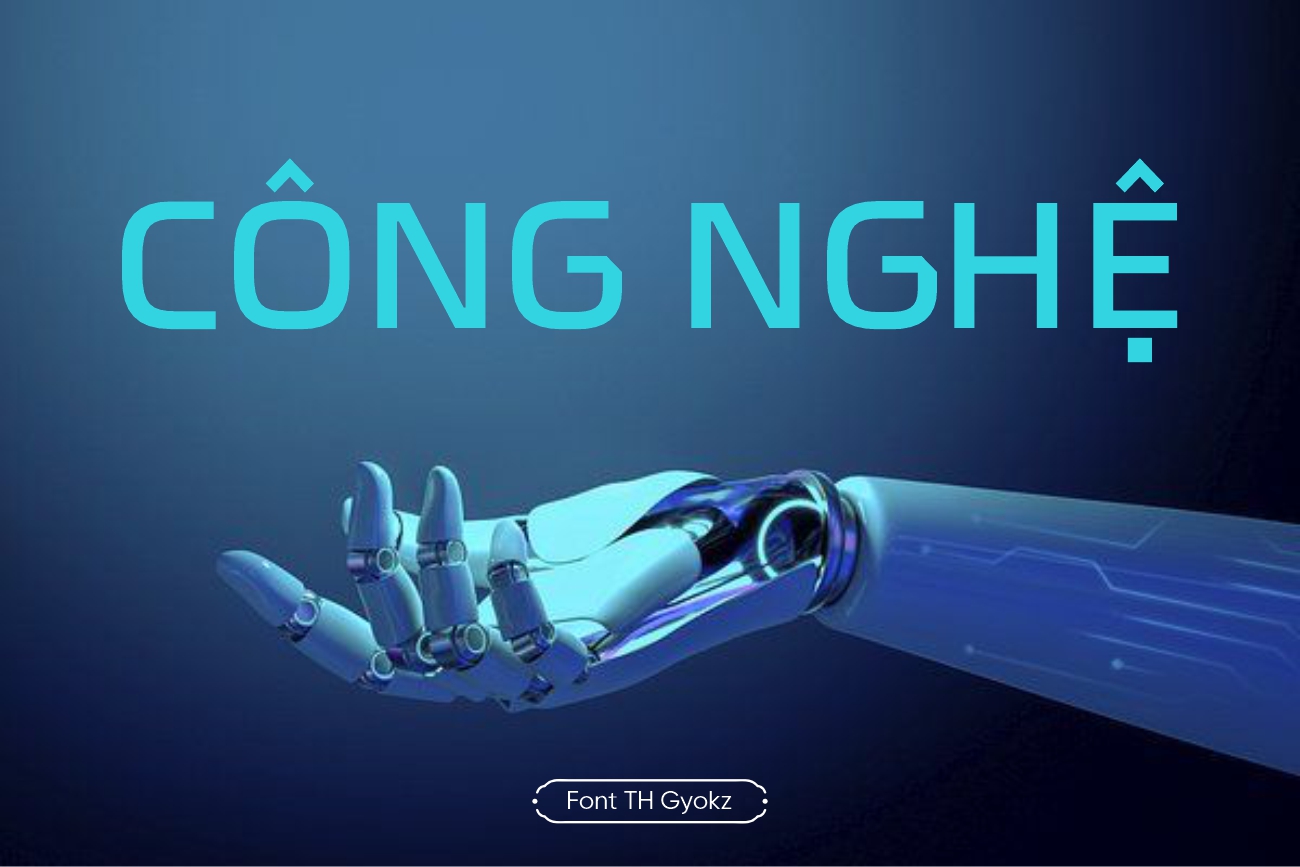
Tải font TH Gyokz nếu anh đang làm nhãn công nghệ, tem bảo hành điện tử, headline nhỏ trên hộp thiết bị. Điểm mạnh của TH Gyokz là có tinh thần công nghệ rõ nhưng vẫn gọn, hợp cho các cụm chữ ngắn như mã series, tên dòng sản phẩm hoặc tem xác thực. Với nhãn kỹ thuật, font này nên được test trên nội dung thật như model, mã sản phẩm, thời hạn bảo hành, hotline, QR code, thông số input/output và dòng cảnh báo.
Khi dùng TH Gyokz, anh nên kiểm tra bản in thử ở kích thước thật. Nếu chữ số, dấu tiếng Việt hoặc ký tự đặc biệt như “/”, “-”, “.”, “V”, “A”, “mAh”, “Hz” vẫn rõ, font có thể dùng cho hệ thống label sản phẩm.
2. TH Wolgen - bao bì thiết bị, nhãn máy móc, tem phụ kiện điện tử và nhãn kỹ thuật cần cảm giác chắc
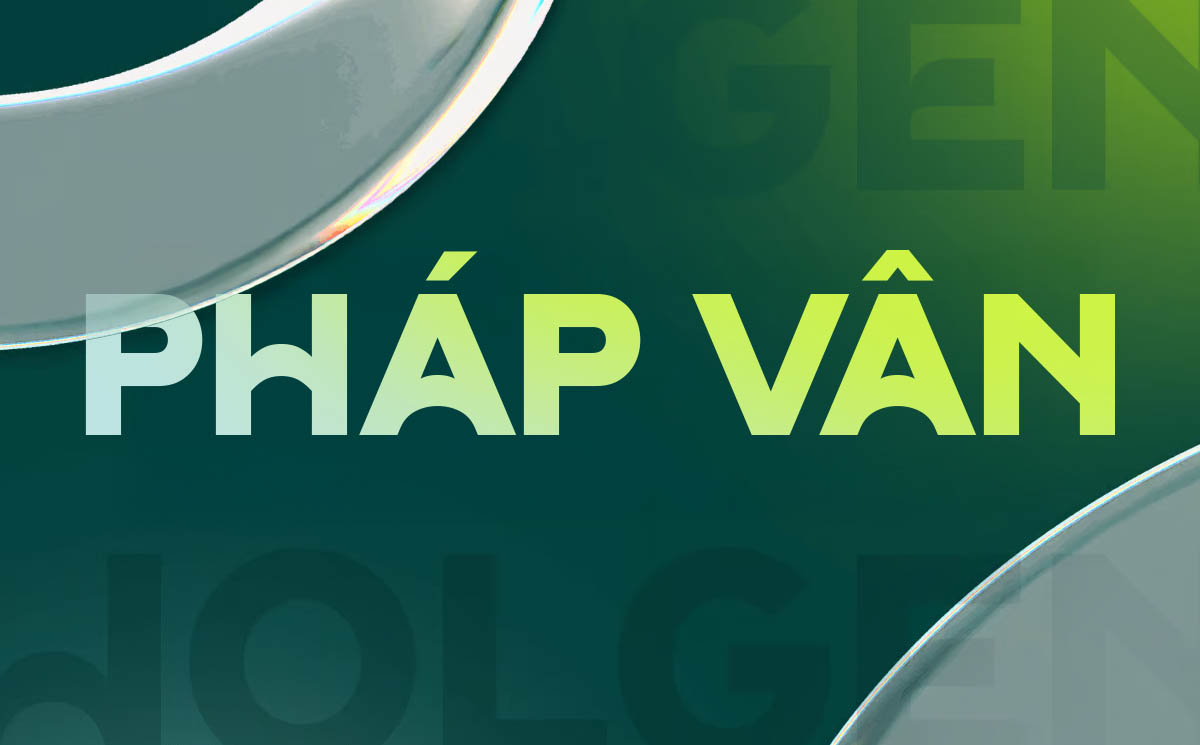
Tải font TH Wolgen nếu anh đang làm bao bì thiết bị, nhãn máy móc, tem phụ kiện điện tử và nhãn kỹ thuật cần cảm giác chắc. Điểm mạnh của TH Wolgen là nét cứng cáp, dễ tạo cảm giác bền, chính xác và phù hợp với sản phẩm kỹ thuật. Với nhãn kỹ thuật, font này nên được test trên nội dung thật như model, mã sản phẩm, thời hạn bảo hành, hotline, QR code, thông số input/output và dòng cảnh báo.
Khi dùng TH Wolgen, anh nên kiểm tra bản in thử ở kích thước thật. Nếu chữ số, dấu tiếng Việt hoặc ký tự đặc biệt như “/”, “-”, “.”, “V”, “A”, “mAh”, “Hz” vẫn rõ, font có thể dùng cho hệ thống label sản phẩm.
3. TH Degrad Mono - mã sản phẩm, barcode label, bảng thông số, QR guide và tem serial
Tải font TH Degrad Mono nếu anh đang làm mã sản phẩm, barcode label, bảng thông số, QR guide và tem serial. Điểm mạnh của TH Degrad Mono là chất mono/công nghệ giúp các chuỗi ký tự, mã SKU và thông số nhìn trật tự hơn. Với nhãn kỹ thuật, font này nên được test trên nội dung thật như model, mã sản phẩm, thời hạn bảo hành, hotline, QR code, thông số input/output và dòng cảnh báo.
Khi dùng TH Degrad Mono, anh nên kiểm tra bản in thử ở kích thước thật. Nếu chữ số, dấu tiếng Việt hoặc ký tự đặc biệt như “/”, “-”, “.”, “V”, “A”, “mAh”, “Hz” vẫn rõ, font có thể dùng cho hệ thống label sản phẩm.
4. TH Artega - nhãn thông tin sản phẩm, hướng dẫn sử dụng ngắn và bao bì tối giản
Tải font TH Artega nếu anh đang làm nhãn thông tin sản phẩm, hướng dẫn sử dụng ngắn và bao bì tối giản. Điểm mạnh của TH Artega là sans-serif tối giản, ít trang trí, phù hợp khi cần trình bày nhiều thông tin trong diện tích nhỏ. Với nhãn kỹ thuật, font này nên được test trên nội dung thật như model, mã sản phẩm, thời hạn bảo hành, hotline, QR code, thông số input/output và dòng cảnh báo.
Khi dùng TH Artega, anh nên kiểm tra bản in thử ở kích thước thật. Nếu chữ số, dấu tiếng Việt hoặc ký tự đặc biệt như “/”, “-”, “.”, “V”, “A”, “mAh”, “Hz” vẫn rõ, font có thể dùng cho hệ thống label sản phẩm.
5. TH Cutta - tem bảo hành, phiếu hướng dẫn, hộp phụ kiện, nhãn pin sạc và tem đổi trả
Tải font TH Cutta nếu anh đang làm tem bảo hành, phiếu hướng dẫn, hộp phụ kiện, nhãn pin sạc và tem đổi trả. Điểm mạnh của TH Cutta là có nhiều kiểu sans hiện đại, tiện để phân cấp giữa tên sản phẩm, nhãn phụ và đoạn lưu ý. Với nhãn kỹ thuật, font này nên được test trên nội dung thật như model, mã sản phẩm, thời hạn bảo hành, hotline, QR code, thông số input/output và dòng cảnh báo.
Font cho tem bảo hành, nhãn kỹ thuật và bao bì điện tử cần sạch, rõ, bền khi in và hỗ trợ tiếng Việt tốt. Một font đẹp nhưng khó đọc ở cỡ nhỏ sẽ không phù hợp với label kỹ thuật. Ngược lại, một font sans-serif gọn, có phân cấp tốt và giữ được chữ số rõ ràng sẽ giúp sản phẩm trông chuyên nghiệp hơn rất nhiều.
Khi chọn font cuối cùng, hãy đặt thử vào đúng layout thật: mặt hộp, tem phụ, nhãn cảnh báo, phiếu bảo hành và bảng thông số. Nếu người dùng đọc nhanh được model, thông số, điều kiện bảo hành và cách liên hệ, font đó đã làm đúng việc của nó.